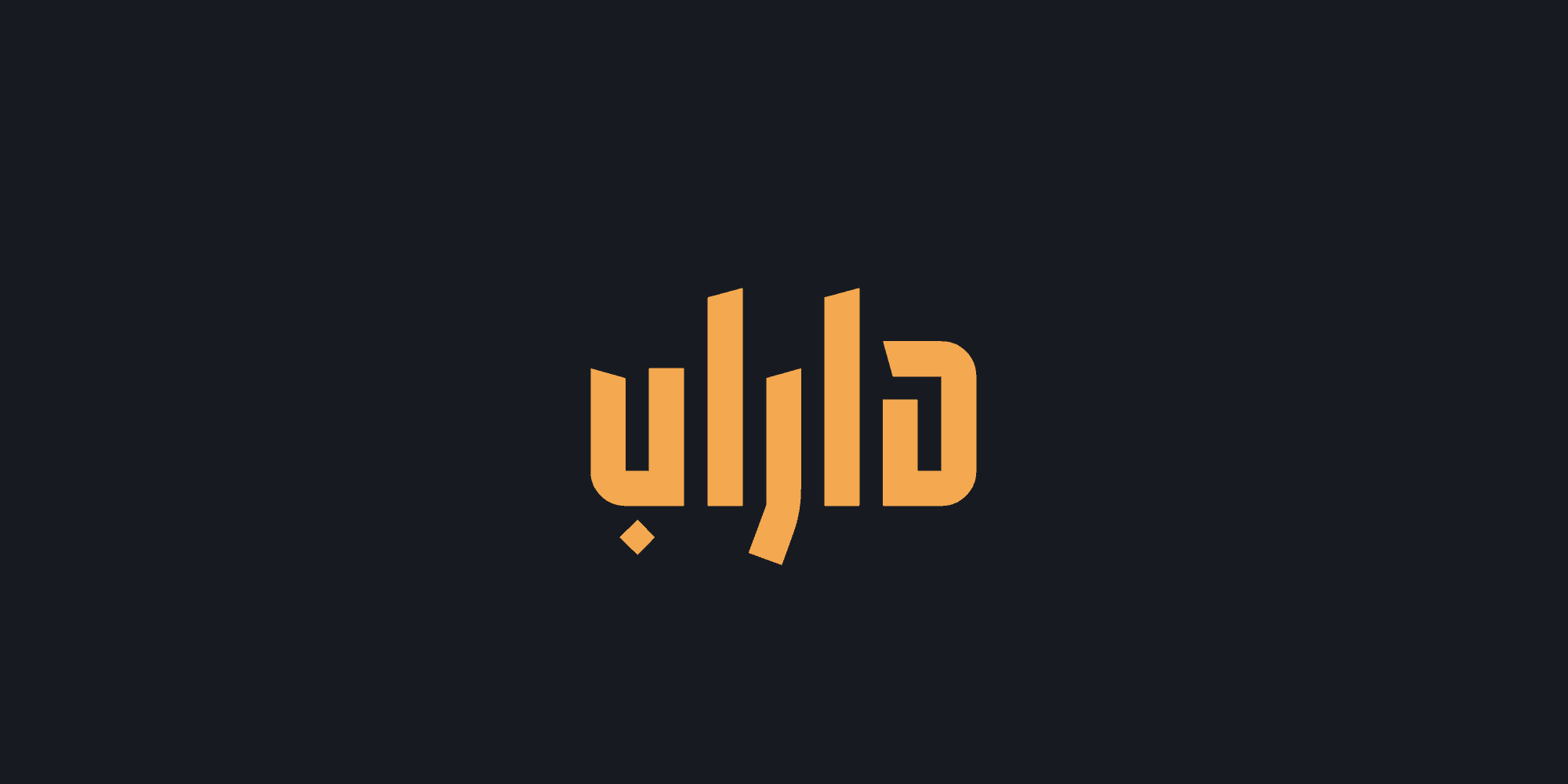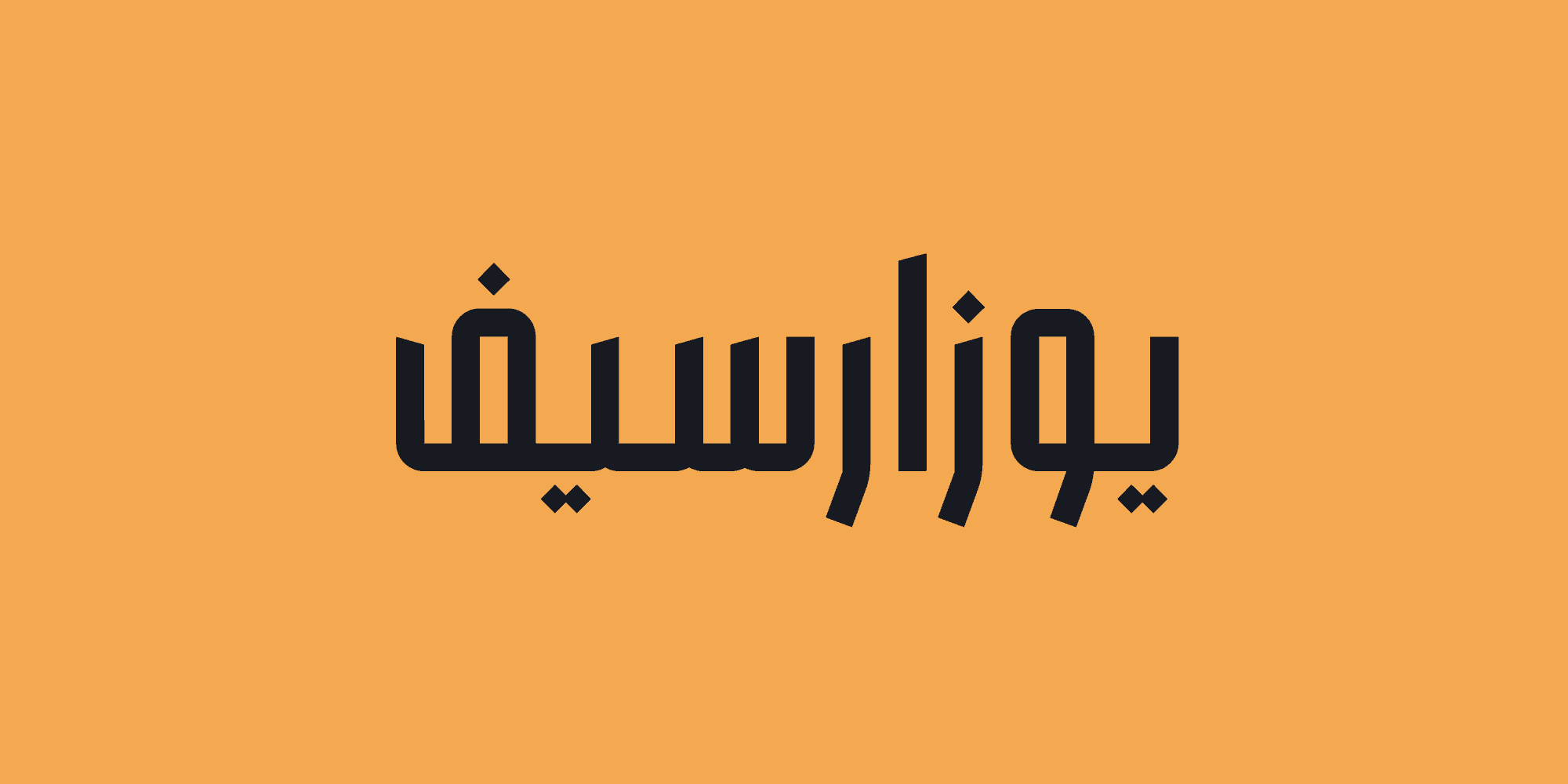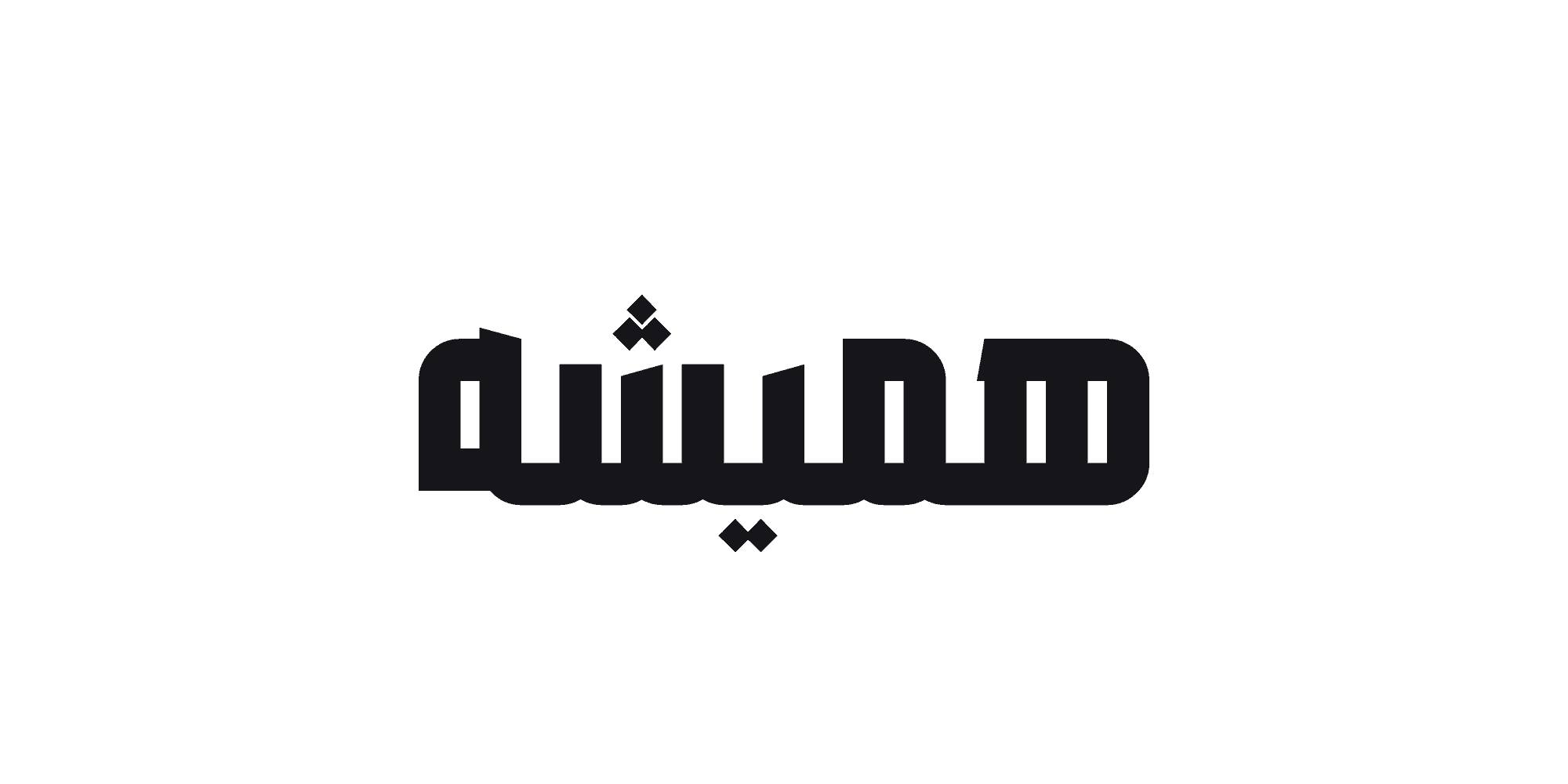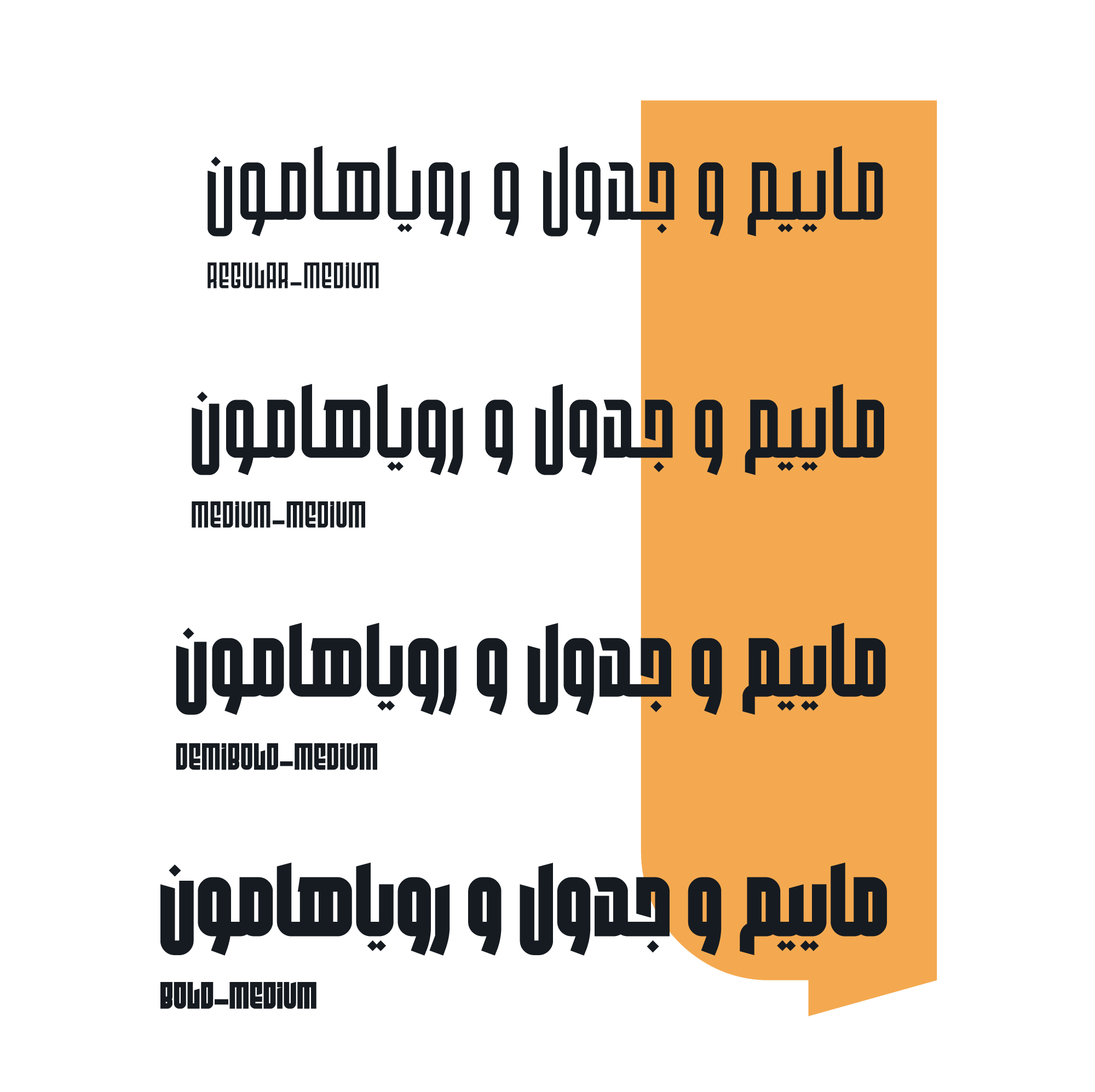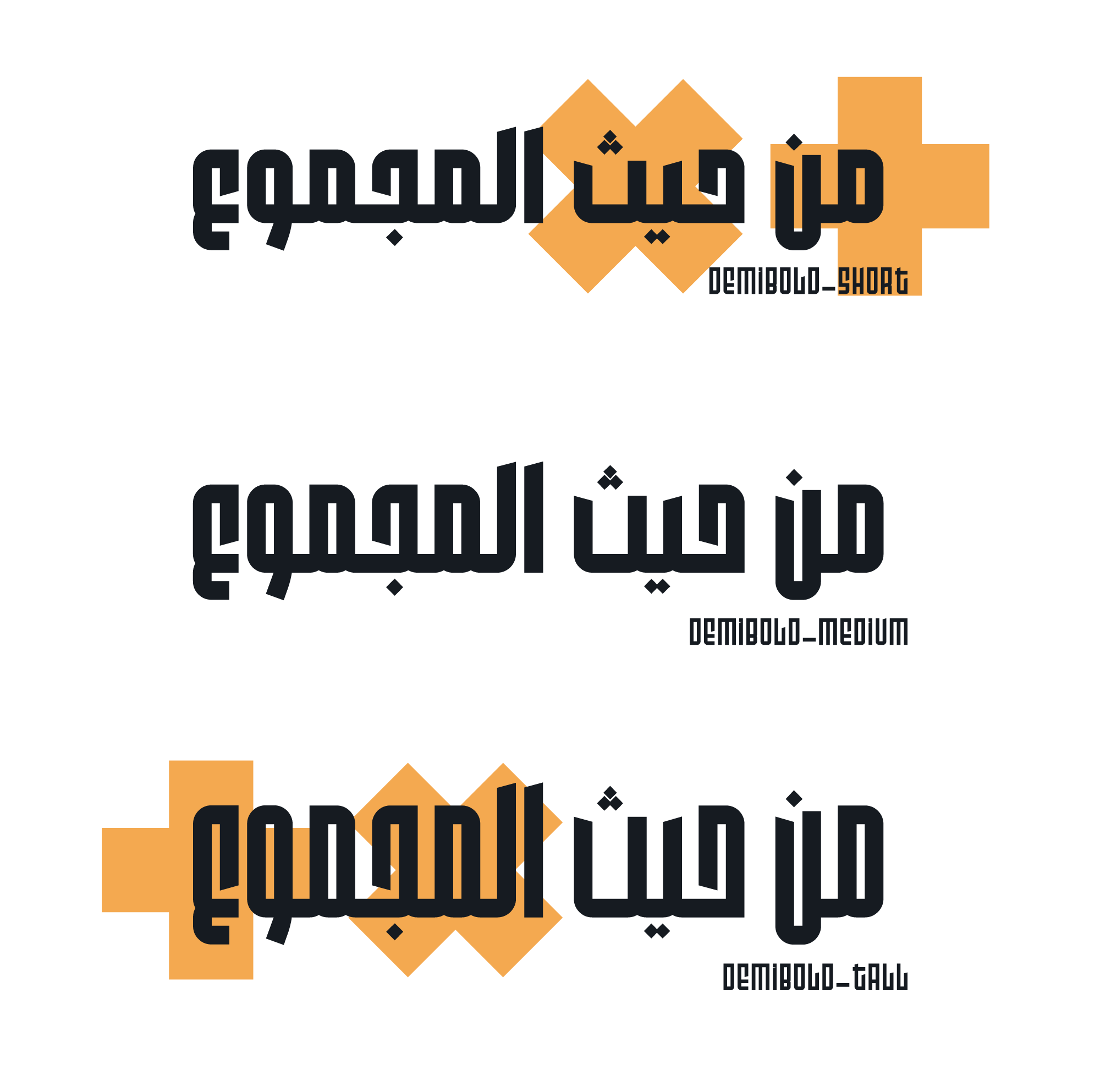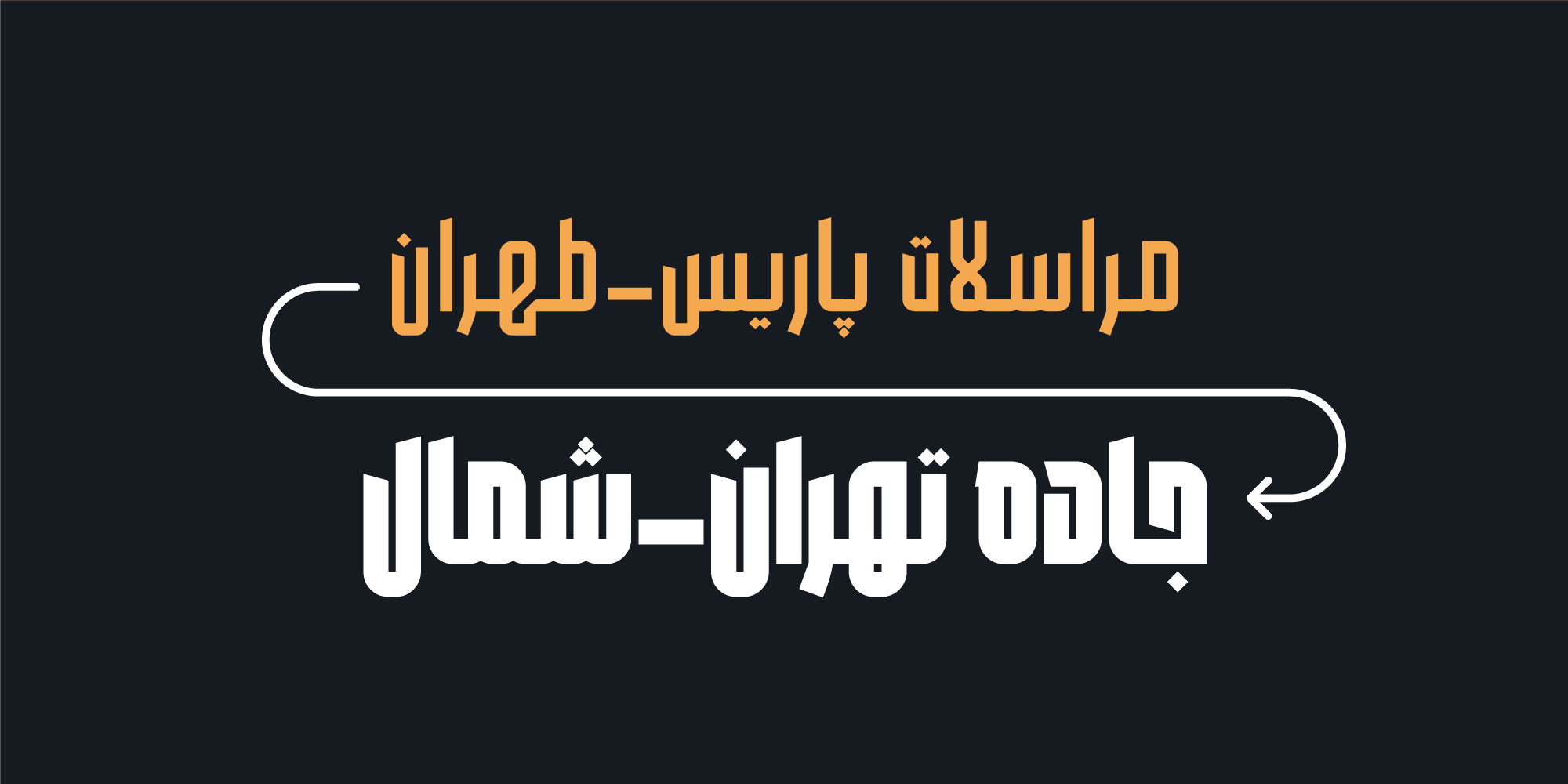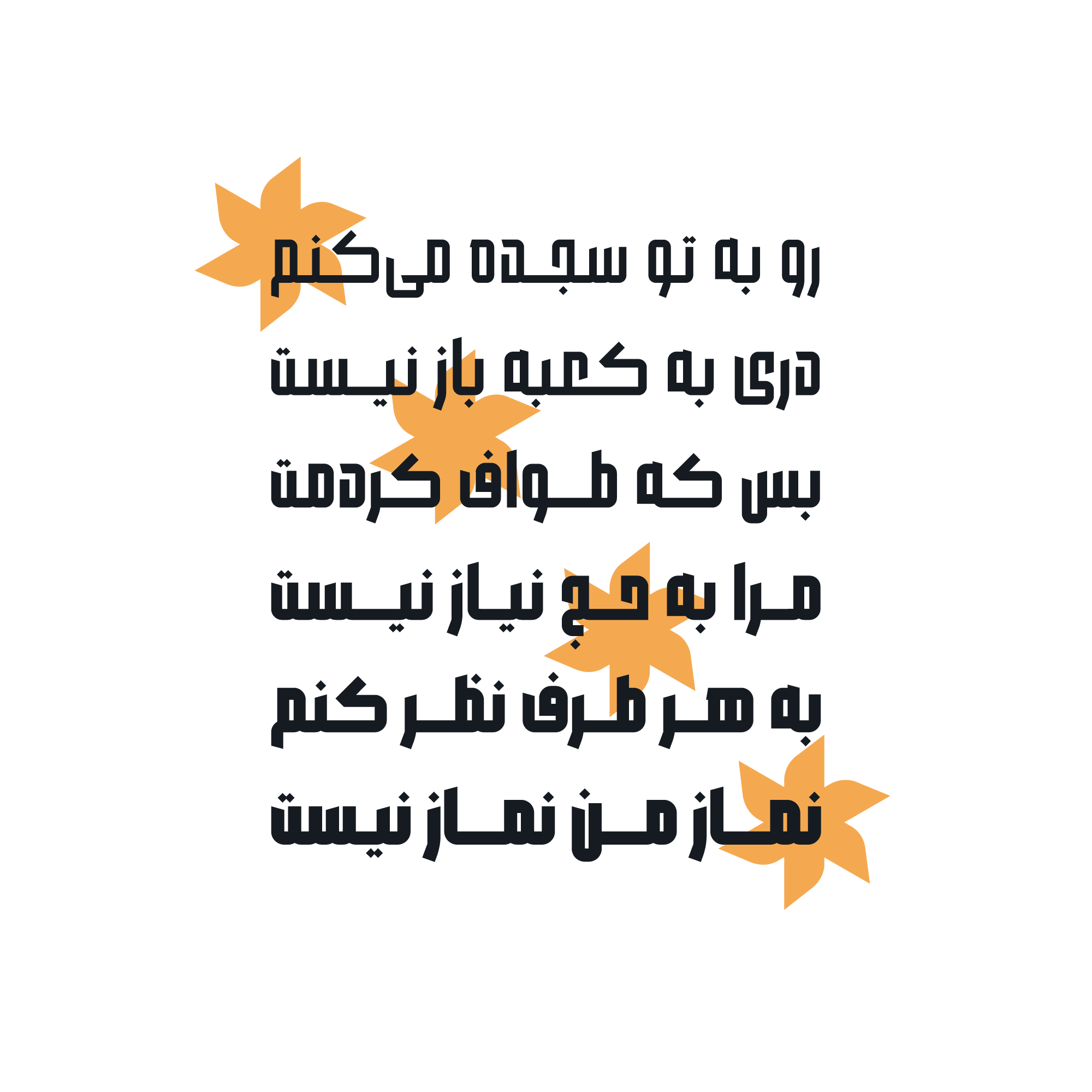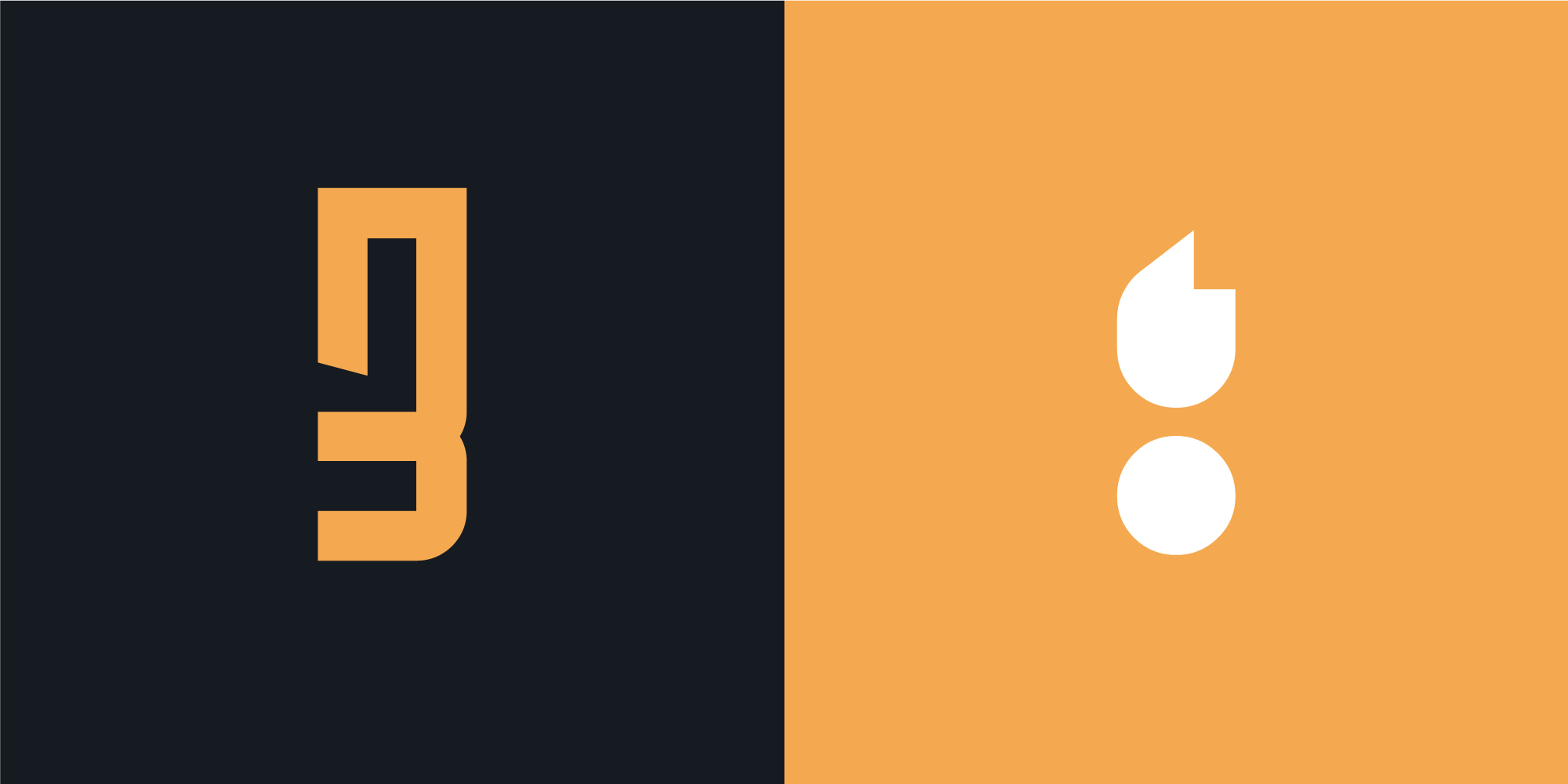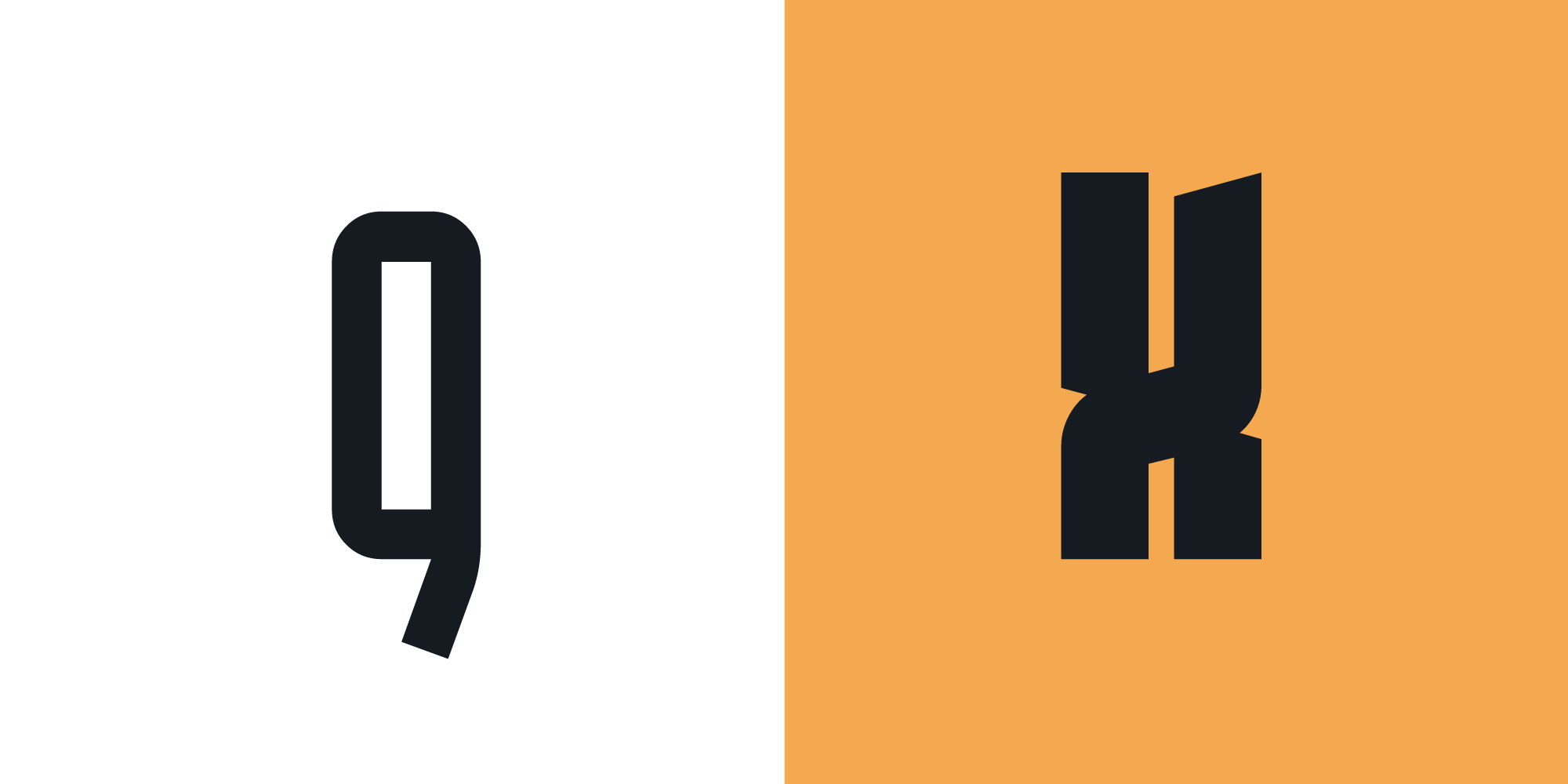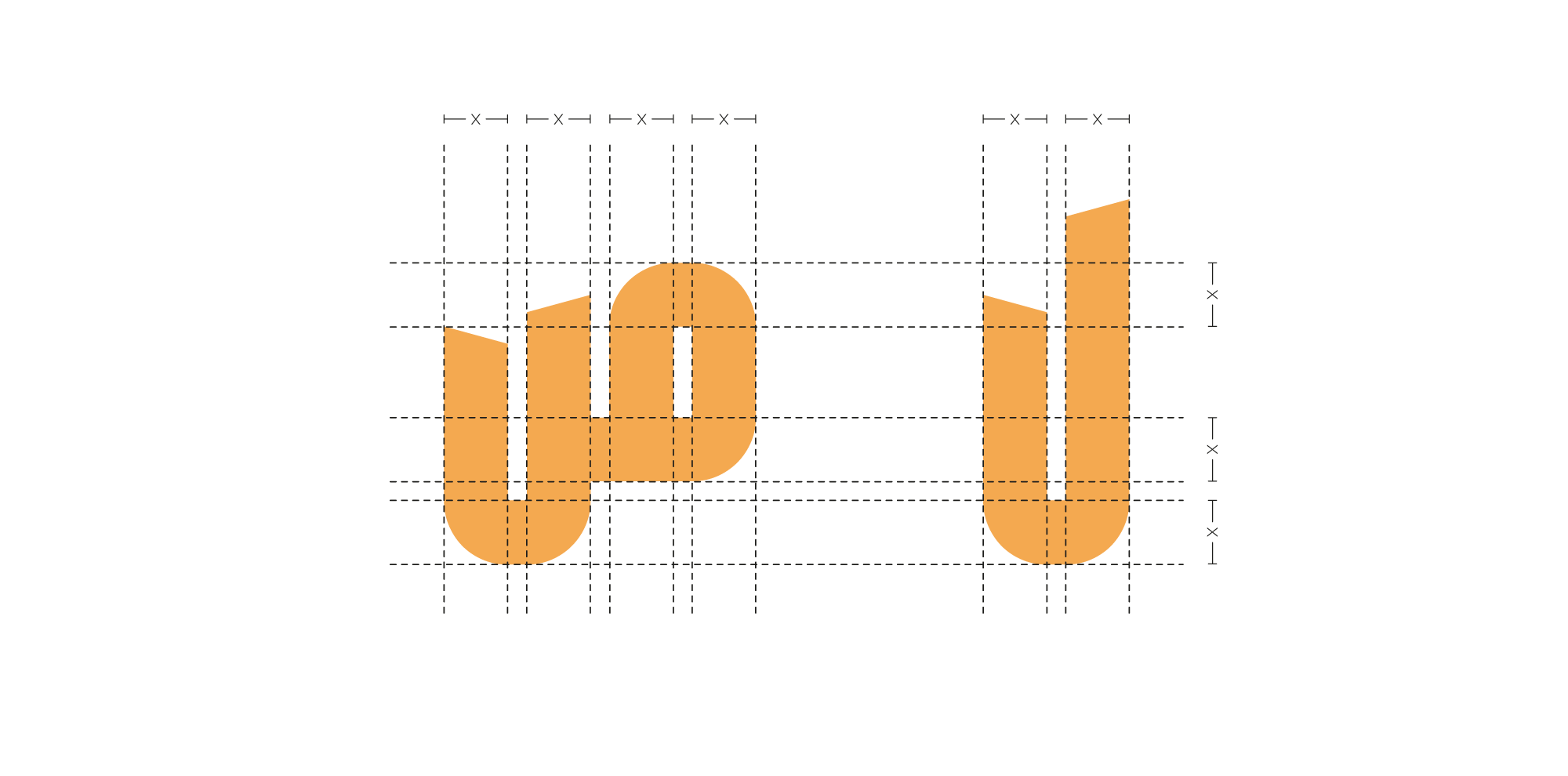
فونت داراب از زبان فارسی، عربی، انگلیسی، اردو و کردی پشتیبانی میکند.
فونت متغیر داراب دارای دو محور تغییر وزن و تغییر ارتفاع حروف است.
فونت داراب در ۴ وزن و ۳ ارتفاع ساخته شده است. یعنی در مجموع شما ۱۲ فونت در اختیار دارید.
ساختار هندسی و هماهنگی ساختمان حروف
ترکیبها و حروف جایگزین
امیرارسلان احمدی متولد ۱۳۸۰ و دانشجوی مهندسی هوافضای دانشگاه صنعتی شریف است که چند سالیست مشغول مطالعه و فعالیت در طراحی گرافیک و به طور متمرکز، طراحی لوگو میباشد. او همچنین در زمینهی تولید محتوای متنی و تصویری برای رسانههای رسمی و غیررسمی تجربه کسب کردهاست.
شهرزاد اکبری، متولد ۱۳۷۰، دانش آموخته کارشناسی کامپیوتر نرمافزار است. شهرزاد تجربه برنامه نویسی با زبانهای مختلف و همچنین تولید محتوا و طراحی برای چند استارتاپ را داشته است. او پس از آشنایی با «توسعه فونت» به عنوان ابزاری برای تلفیق هنر و علم برنامه نویسی به این حوزه علاقهمند شده و در آن مشغول به فعالیت شده است.